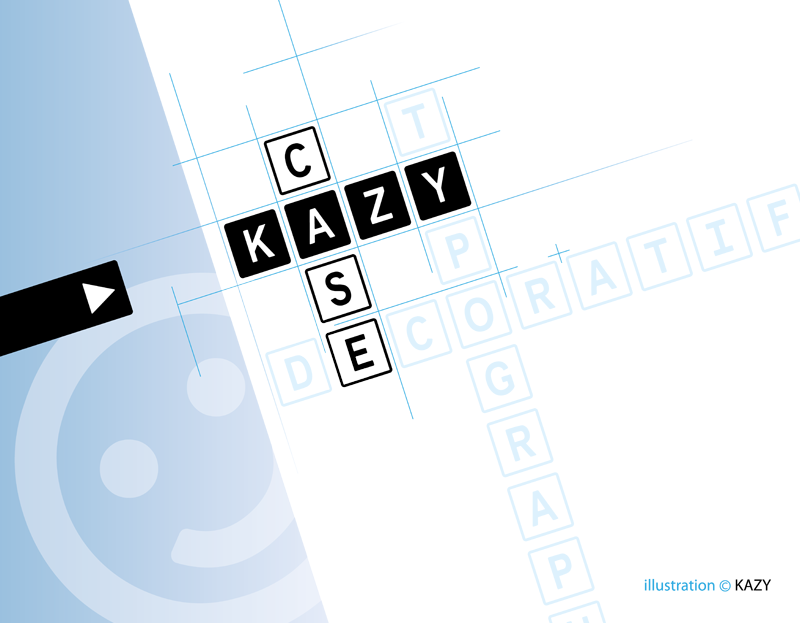
Preview and download KazyCase Font. Created by Emmanuel Didier in Fancy Decorative styles with Shareware license.
�KAZYcase� est une police originale et ludique. Vous trouverez les carr�s noirs avec le texte en blanc � l�aide de la touche majuscule du clavier. Dans les glyphes se trouvent de nombreuses lettres avec des accents et symboles utilisables dans de nombreux pays diff�rents. �KAZYcase� est une police shareware�! Vos projets personnels avec commission ou profit avec cette police ne sont pas autoris�s sans licence. Pour une utilisation commerciale, vous trouverez la version de �KAZYcase� avec licence ici : https://www.creativefabrica.com/de/designer/kazy//ref/895942 Merci pour votre soutien. Bien � vous. Kazy ___________________ �KAZYcase� is an original and fun font. You will find the black squares with the white text using the shift key on the keyboard. Within the glyphs are many letters with accents and symbols that can be used in many different countries. �KAZYcase� is a shareware font! Your personal projects with commission or profit with this font are not allowed without a license. For commercial use you will find the licensed version of �KAZYcase� here: https://www.creativefabrica.com/de/designer/kazy//ref/895942 Thank you for your support. Yours truly. Kazy |